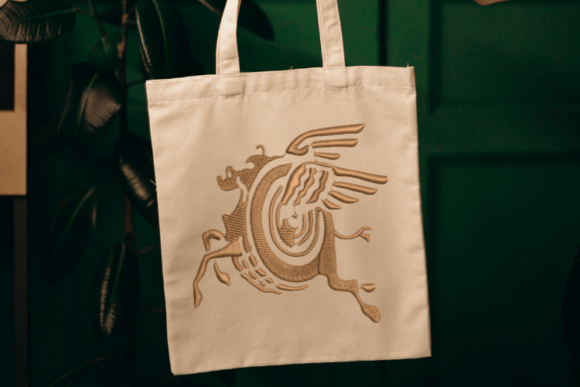
Timeless Elegance Embroidery Design
การค้นหาองค์ประกอบการออกแบบที่เหมาะสมอาจเป็นเรื่องท้าทาย แต่ Timeless Elegance Embroidery Design นำเสนอคอลเลกชันที่โดดเด่นซึ่งช่วยยกระดับงานของคุณได้ทันที
สร้างขึ้นอย่างแม่นยำ Timeless Elegance Embroidery Design ให้เวกเตอร์ที่สะอาด พิมพ์ตัวอักษรที่ราบรื่น และใบอนุญาตเชิงพาณิชย์เพื่อความสบายใจ
ไม่ว่าคุณจะสร้างผลิตภัณฑ์ POD (Print on Demand) คำเชิญงานแต่งงาน หรือกราฟิกโซเชียลมีเดีย Timeless Elegance Embroidery Design ก็เหมาะสมอย่างยิ่ง